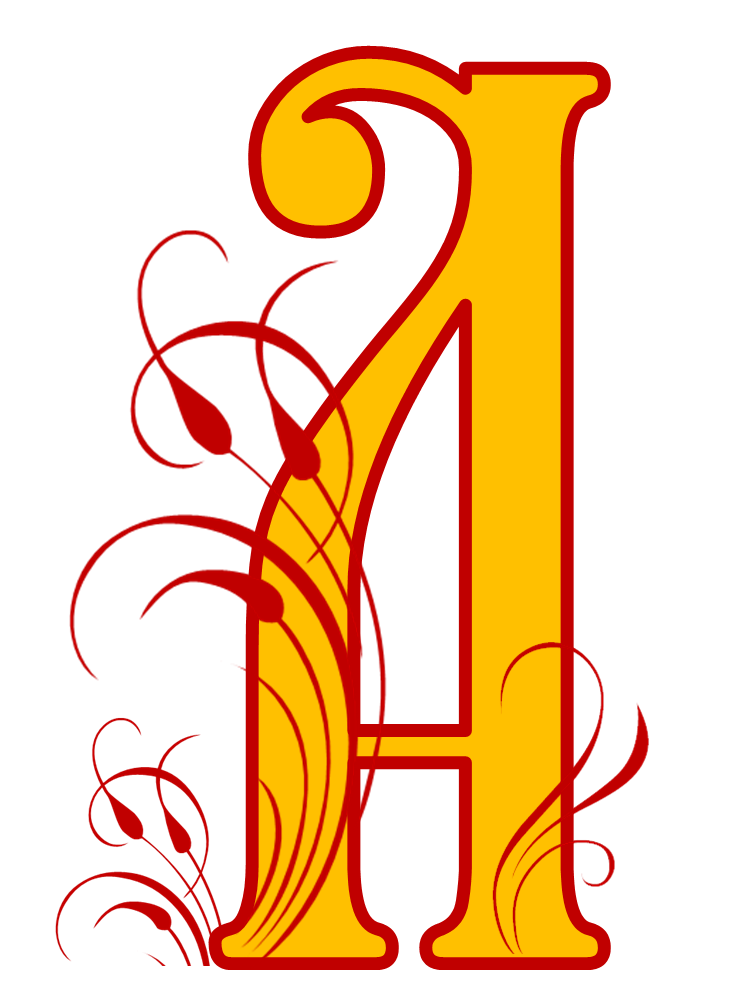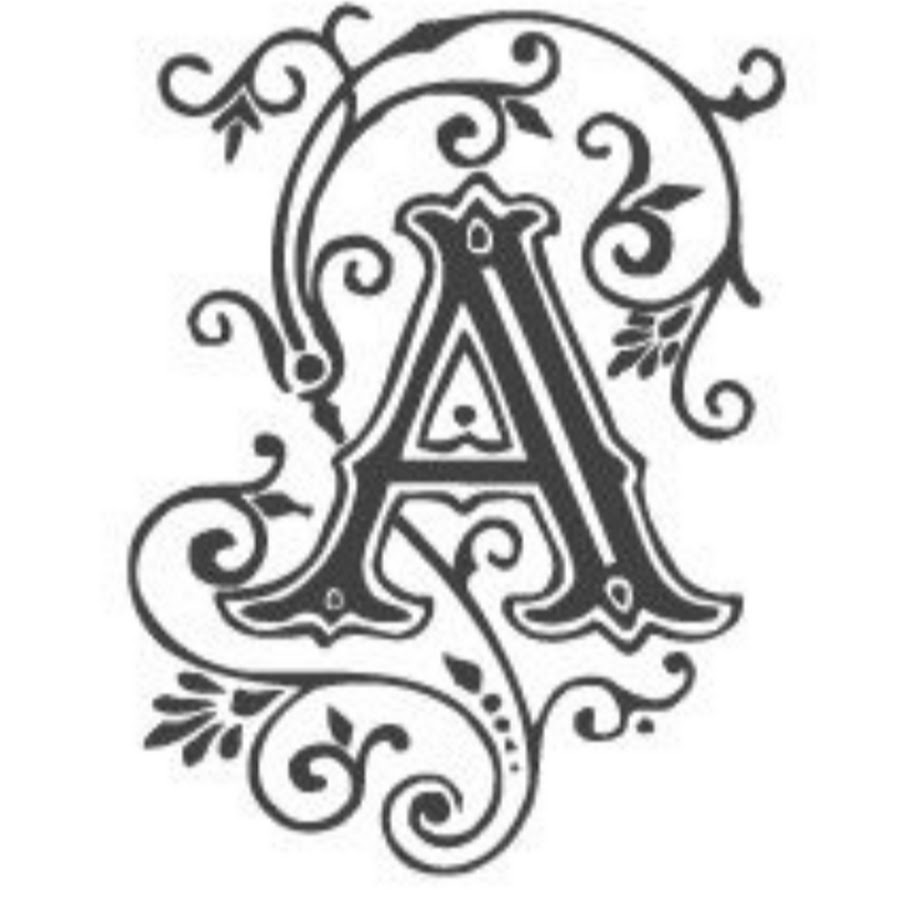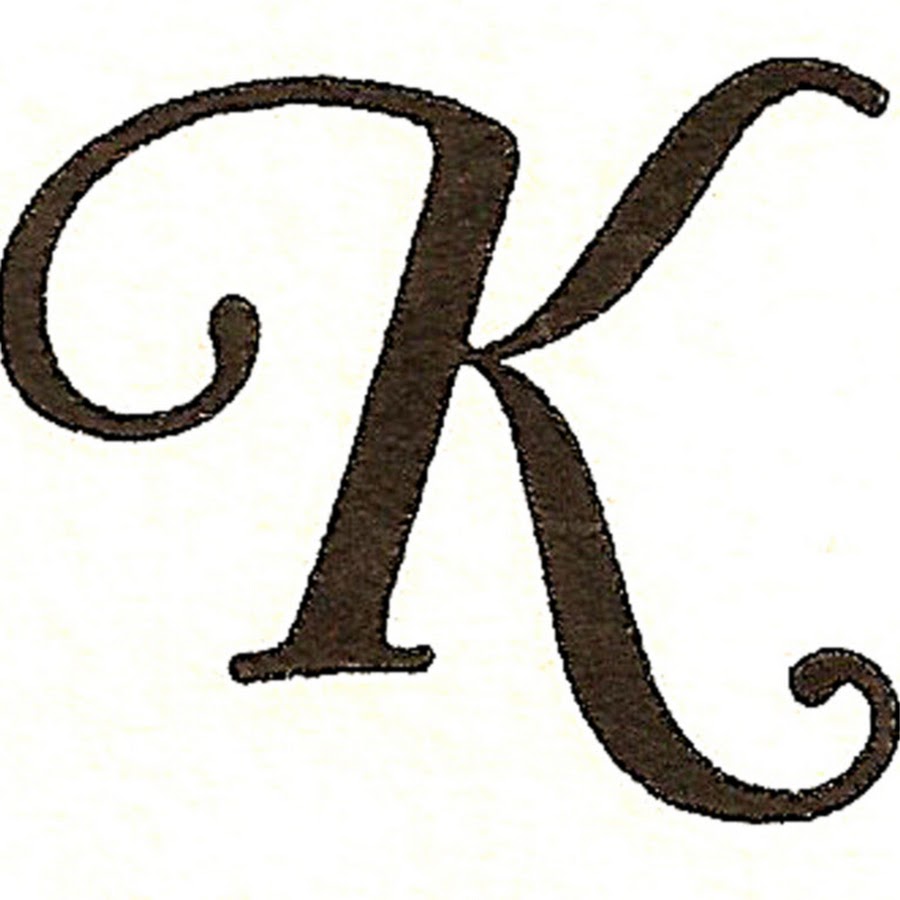
Красивые прописные буквы ➡️ Конвертер красивых прописных букв
— Красивые заглавные буквы. Оказывается, есть способ добавить стилизованные буквы, которые на самом деле являются специальными символами, а также смайлики и другие символы. На практике они выглядят как пользовательские шрифты, но технически называются
Когда вы вводите или вставляете слова, отобразит список вашего стилизованного фрагмента в разных шрифтах. Если вам нужно больше альтернатив, просто нажмите «загрузить больше шрифтов».
3. Скопируйте текст желаемым шрифтом.
Помните, что в Instagram нет возможности редактировать источник. Что мы сделаем, так это сохраним последовательность символов, а затем перенесем их в нужное поле.
Поэтому выберите текст с тем шрифтом, который вы хотите использовать, и используйте команду копирования на вашем устройстве.
4. Instagram, Facebook, Twitter, Youtube, WhatsApp, Twitch, TikTok или любая социальная сеть.
Теперь, когда ваш текст сохранен в буфере обмена вашего ПК или телефона, используйте команду
Хорошие прописные буквы. Помните, что может произойти некоторая несовместимость символов Unicode.
Таким образом, убедитесь, что фрагмент отображается так, как ожидалось И если да, отрегулируйте его, чтобы не удивлять своих подписчиков.
Наконец, мы рекомендуем вам выбрать один или два из этих шрифтов для частого использования, чтобы они Отличительная черта ваших постов.
Поэтому попробуйте использовать шрифты, чтобы обогатить внешний вид подписей, которые вы пишете для изображений.
И не забывай используйте стилизованные буквы в биографии профиля, если вы сочтете это подходящим. Используйте эту функцию, чтобы привлечь тех, кто еще не подписан, а также побудить тех, кто уже подписан на вас, предпринять определенные действия.